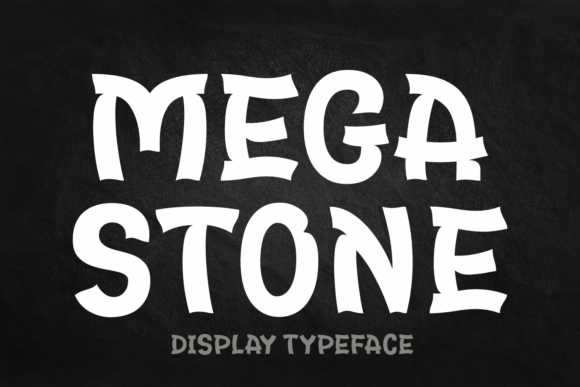
Mega Stone Font – الخط المثالي لإضافة لمسة قوية وجريئة إلى تصاميمك!
استمتع بتجربة تصميم فريدة مع Mega Stone Font، الخط المستوحى من الأحجار الصلبة والقوام الطبيعي، والذي يمنح تصاميمك إحساسًا بالقوة والصلابة. يتميز الخط بتفاصيله الحادة وهيكله القوي، مما يجعله الخيار الأمثل للعناوين البارزة، والشعارات الاحترافية، والتصميمات التي تحتاج إلى طابع جريء ولافت للنظر.
✅ تصميم احترافي مستوحى من الصخور والأحجار
✅ مناسب للعناوين، الشعارات، والتصميمات القوية
✅ مثالي للمشاريع الإبداعية والتجارية
اجعل تصاميمك تنطق بالقوة والتميز مع Mega Stone Font! ????